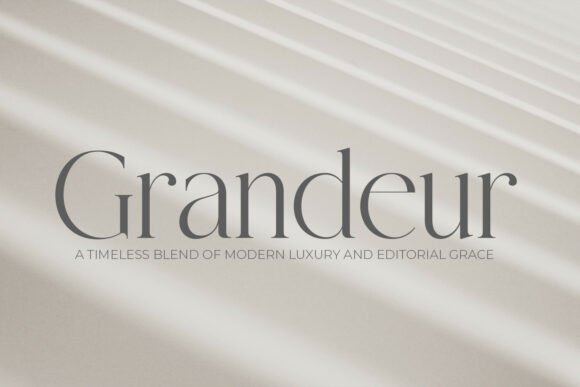
Grandeur – Elegant Classic Serif
Trovare i giusti elementi di design può essere difficile, ma Grandeur – Elegant Classic Serif offre una collezione eccezionale che eleva istantaneamente il tuo lavoro.
Che tu stia creando prodotti POD (Print on Demand), partecipazioni di nozze o grafiche per i social media, Grandeur – Elegant Classic Serif è la scelta ideale.